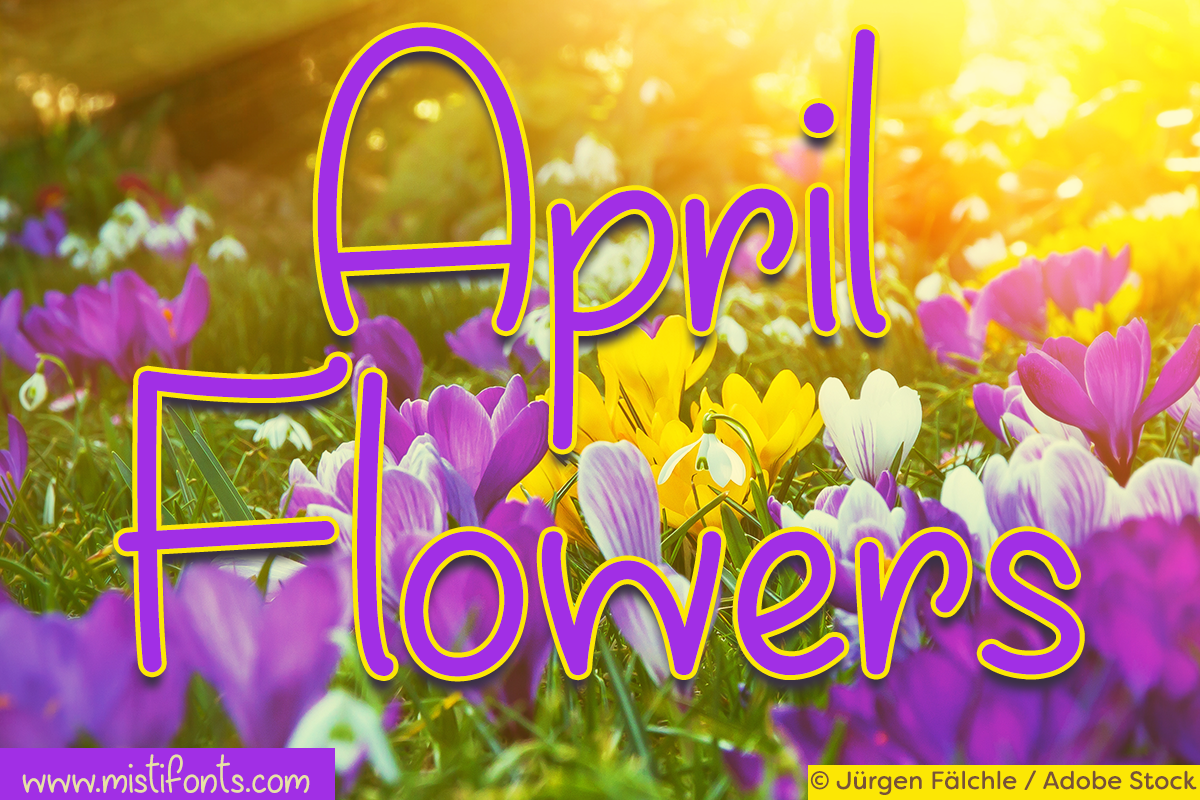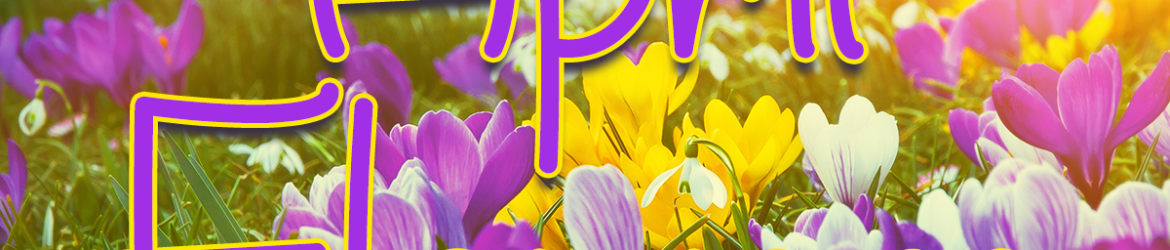
April Flowers Font – Download Grátis
A font April Flowers é perfeita para quem busca uma mão-dupla delicada e elegante, ideal para aplicativos de mensagens ou até mesmo desenhos pessoais. Criada por Misti’s Fonts, essa fonte é especialmente indicada para designers que valorizam a liberdade criativa sem sacrificar o uso comercial. O designer Misti nos oferece uma fonte livre e disponível apenas para uso pessoal e não-profit. Quem decide usá-la em projetos comerciais deve adquirir um licenciamento. Assim, se você usa esta fonte no seu dia a dia e deseja manter o uso pessoal, pode fazê-lo sem problema algum. Para aqueles que valorizam mais uma font de negócios, existem opções pagas. Em qualquer caso, April Flowers é uma adição incrível ao seu arsenal de recursos gráficos, proporcionando um toque delicado e único em suas criações digitais.